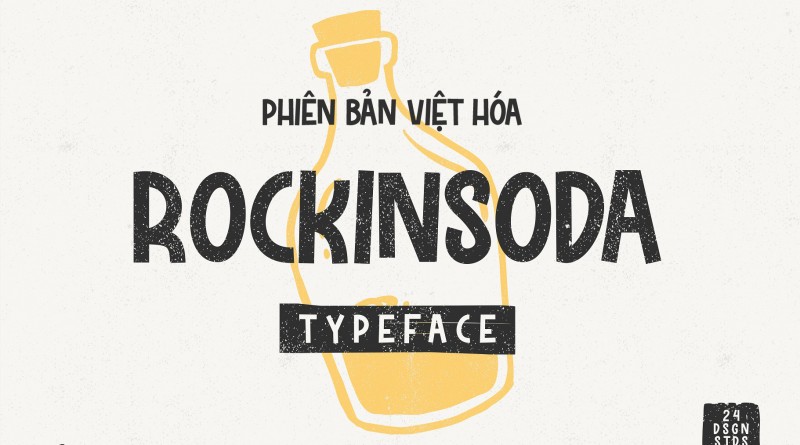
Font việt hóa FS Rockinsoda
Font việt hóa FS Rockinsoda – Bộ font chữ Retro đầy phong cách cho thiết kế
Giới thiệu về Font việt hóa FS Rockinsoda
Trong thế giới thiết kế đồ họa hiện nay, việc lựa chọn một Font Miễn Phí có phong cách độc đáo luôn là ưu tiên hàng đầu của các bạn học sinh và thầy cô giáo khi làm bài thuyết trình. Font việt hóa FS Rockinsoda nổi lên như một lựa chọn hoàn hảo nhờ sự kết hợp tinh tế giữa nét cổ điển Retro và hơi thở hiện đại. Đây là bộ phông chữ được tinh chỉnh kỹ lưỡng để phù hợp với bảng mã tiếng Việt, giúp người dùng không còn lo lắng về lỗi hiển thị dấu khi soạn thảo nội dung sáng tạo.
Đặc điểm nổi bật của Font việt hóa FS Rockinsoda
Phong cách thiết kế độc đáo
FS Rockinsoda mang trong mình những đường nét bo tròn mềm mại nhưng vẫn giữ được sự mạnh mẽ, cá tính. Kiểu dáng này gợi nhớ đến những tấm biển quảng cáo từ thập niên 80, tạo nên cảm giác gần gũi và thân thiện. Khi sử dụng Font việt hóa FS Rockinsoda, các sản phẩm như bìa báo tường, thiệp mời hay logo lớp học sẽ trở nên ấn tượng và có sức hút riêng biệt hơn bao giờ hết.
Khả năng ứng dụng đa dạng
Không chỉ dừng lại ở các ấn phẩm in ấn, bộ font này còn hoạt động cực kỳ mượt mà trên các nền tảng số như Canva, Photoshop hay PowerPoint. Sự linh hoạt của nó cho phép bạn sáng tạo không giới hạn từ tiêu đề chính cho đến các đoạn văn bản ngắn cần sự phá cách.
Để tận dụng tối đa vẻ đẹp của Font việt hóa FS Rockinsoda, bạn nên kết hợp nó với những gam màu rực rỡ hoặc các hiệu ứng đổ bóng vintage. Hãy đảm bảo rằng bạn đã giải nén tệp tin và cài đặt đúng vào hệ thống máy tính để các phần mềm văn phòng có thể nhận diện ngay lập tức. Đây thực sự là món quà tuyệt vời dành cho cộng đồng thiết kế tại Việt Nam.